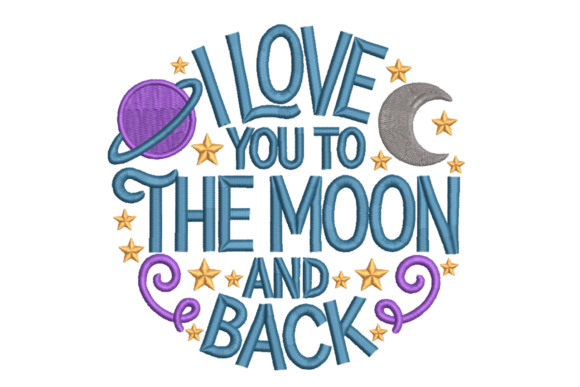
I Love You to the Moon
قد يكون العثور على عناصر التصميم المناسبة أمرًا صعبًا، ولكن I Love You to the Moon يقدم مجموعة استثنائية ترتقي بعملك على الفور.
سواء كنت تقوم بإنشاء منتجات الطباعة عند الطلب أو دعوات الزفاف أو رسومات وسائل التواصل الاجتماعي، فإن I Love You to the Moon هو الخيار المثالي.